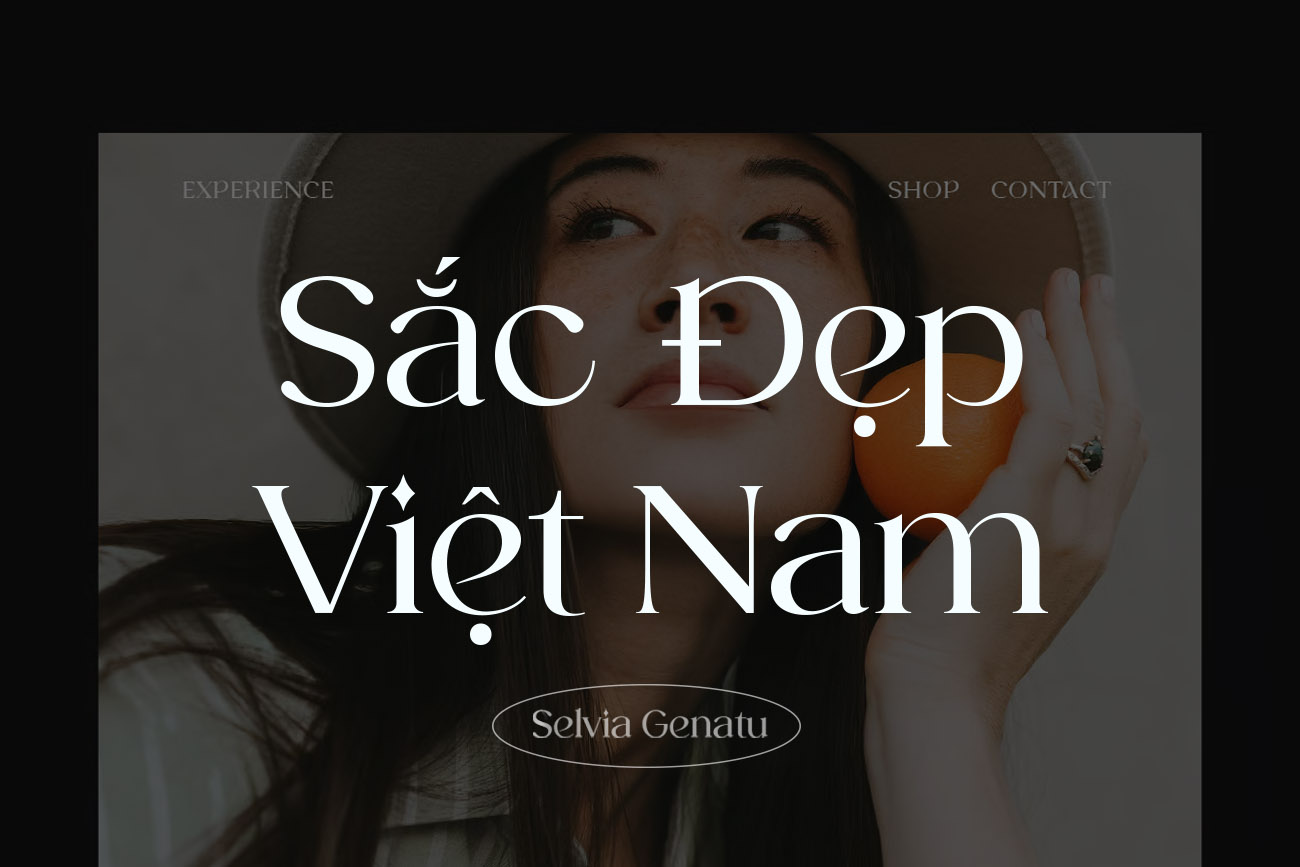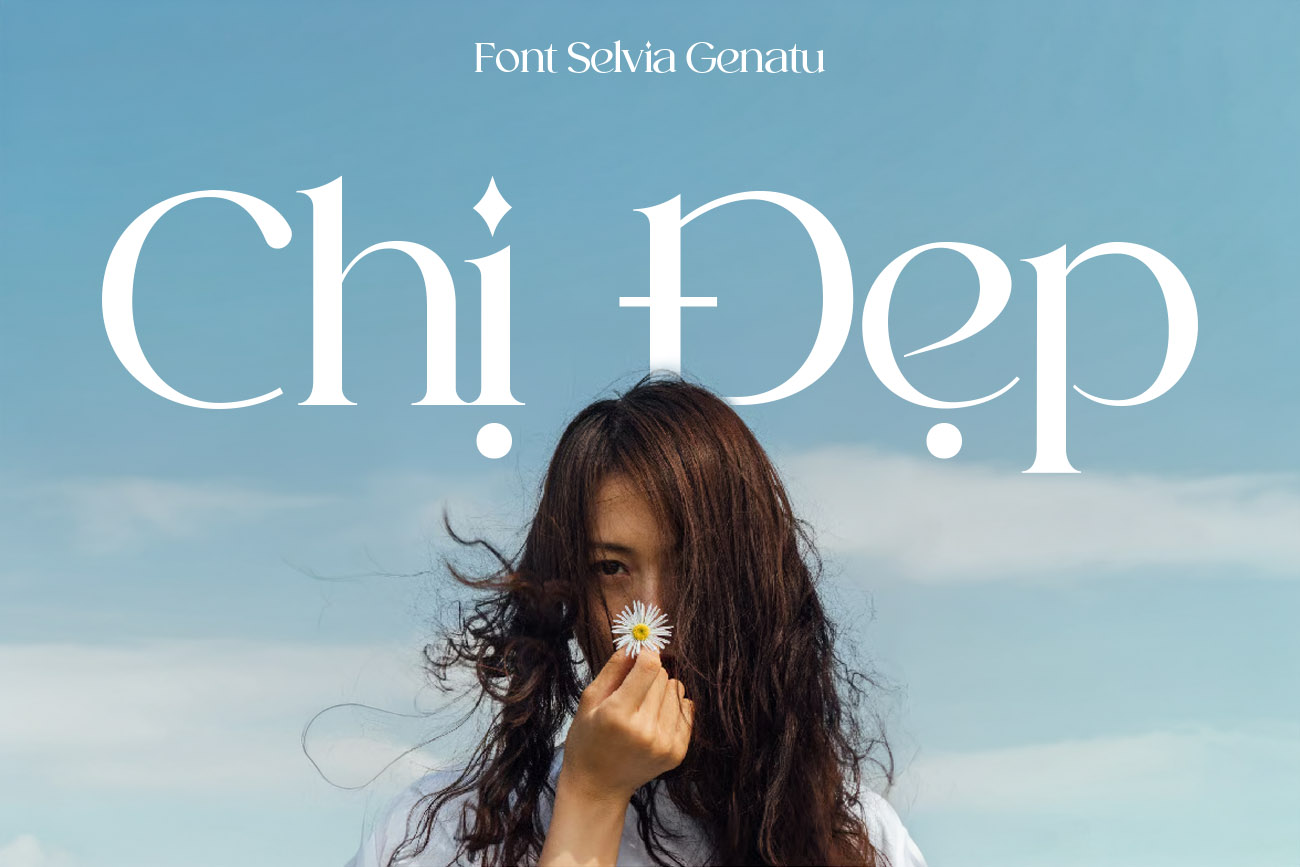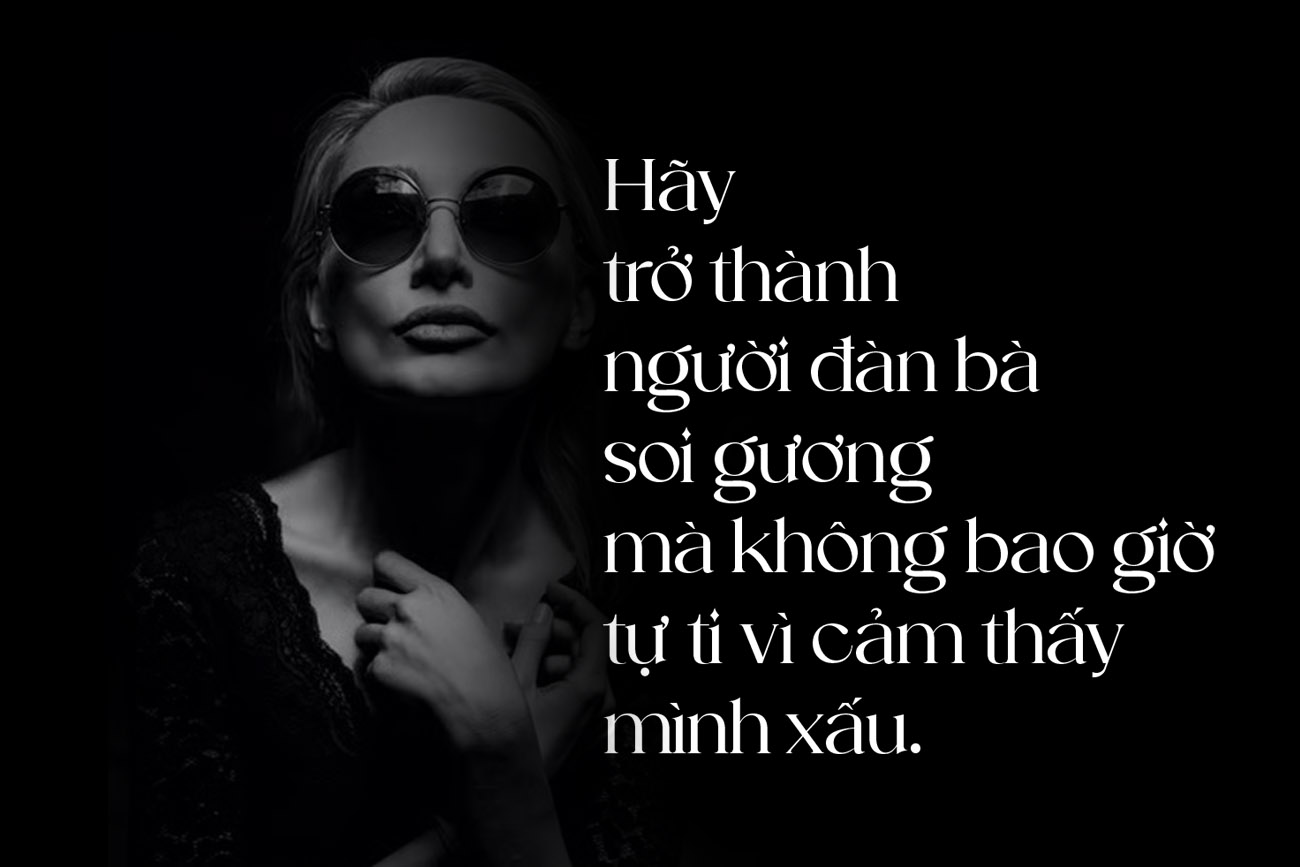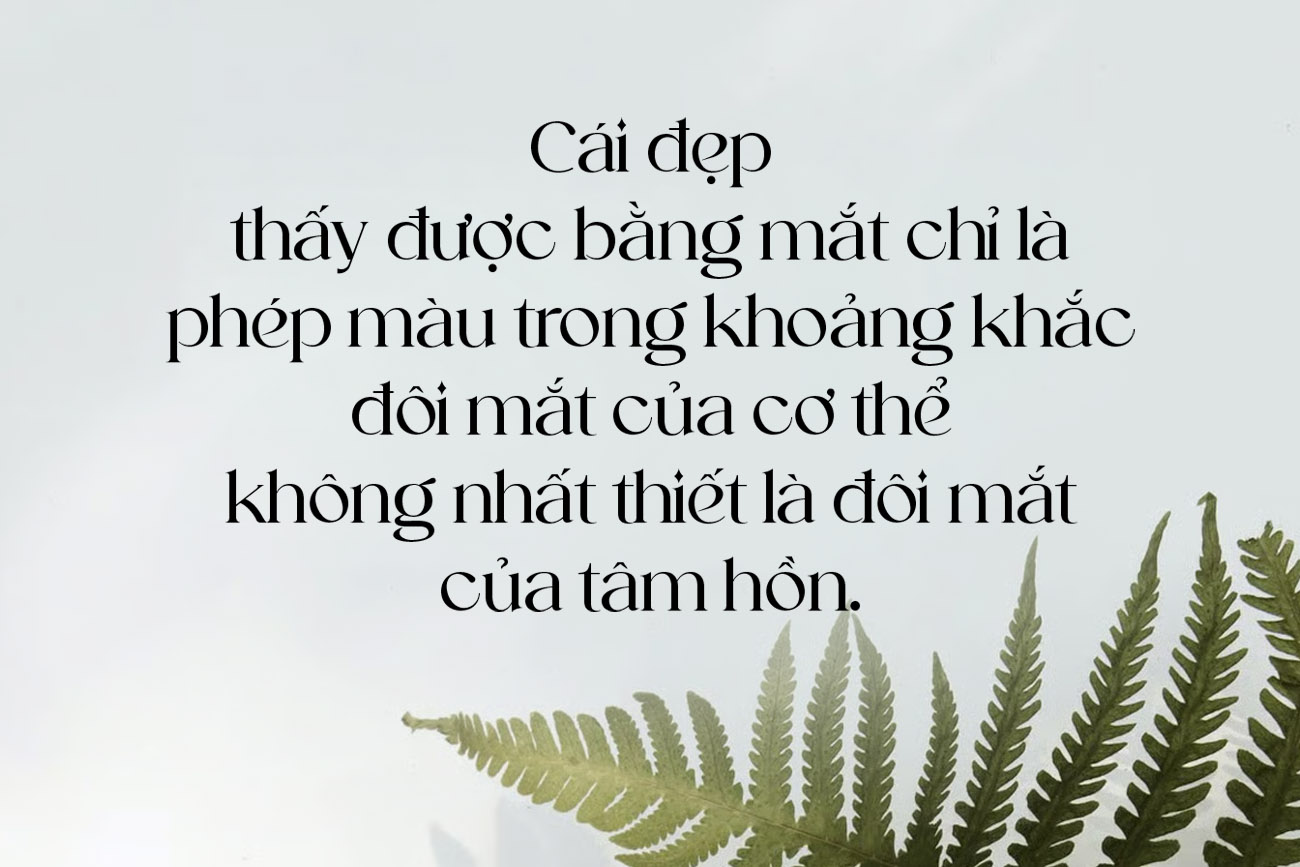
TH Selvia Genatu - Font chữ Serif Việt hóa cho thiết kế sang trọng
Trong thế giới thiết kế đồ họa không ngừng biến đổi, việc tìm kiếm một kiểu chữ vừa mang nét vintage, vừa đáp ứng được xu hướng thẩm mỹ đương đại là điều mà mọi Designer đều mong muốn. Hôm nay, chúng tôi xin giới thiệu đến cộng đồng sáng tạo bộ font chữ Việt hóa TH Selvia Genatu – một tác phẩm đầy tinh tế được Việt hóa bởi Team TH.
TH Selvia Genatu - Tuyệt phẩm Font chữ Serif Việt hóa cho thiết kế sang trọng
Vẻ đẹp giao thoa của Selvia Genatu
Được sáng tạo bởi Yukita Creative, Selvia Genatu nguyên bản là một đại diện xuất sắc cho dòng font chữ Serif (chân có gạch). Khác với những kiểu chữ Serif truyền thống có phần cứng nhắc, Selvia Genatu sở hữu những đường nét thanh mảnh, uyển chuyển với độ tương phản cao giữa các nét thanh và nét đậm.
Đây là một font chữ hiện đại mang trong mình hơi thở của sự sang trọng và đẳng cấp. Các ký tự được thiết kế với những đường cong mềm mại, kết hợp cùng các nét nối (ligatures) độc đáo, tạo nên một tổng thể hài hòa, tựa như những dải lụa lướt nhẹ trên bản thiết kế. Chính vì vậy, Selvia Genatu cực kỳ phù hợp cho các dự án yêu cầu tính thẩm mỹ cao như: thiết kế logo thương hiệu thời trang, tạp chí, thiệp cưới, bao bì mỹ phẩm hay các tiêu đề website cần sự ấn tượng.
TH Selvia Genatu - Tuyệt phẩm Font chữ Serif Việt hóa cho thiết kế sang trọng
Phiên bản Việt hóa hoàn chỉnh từ Team TH
Mặc dù phiên bản gốc từ Yukita Creative đã rất xuất sắc, nhưng rào cản ngôn ngữ thường khiến các Designer Việt gặp khó khăn khi xử lý các dấu câu. Hiểu được điều này, Team TH đã thực hiện việt hóa bộ phông chữ này dưới tên gọi TH Selvia Genatu.
Điểm đặc biệt của phiên bản font chữ Việt hóa này nằm ở sự chỉn chu trong từng dấu tiếng Việt. Team TH không chỉ đơn thuần là thêm dấu, mà còn tinh chỉnh lại khoảng cách (kerning) và vị trí đặt dấu sao cho cân đối nhất với cấu trúc đặc trưng của bộ font gốc. Điều này đảm bảo rằng khi bạn gõ tiếng Việt, dòng chảy của văn bản vẫn giữ được sự liền mạch và tính nghệ thuật vốn có của Selvia Genatu.
TH Selvia Genatu - Tuyệt phẩm Font chữ Serif Việt hóa cho thiết kế sang trọng
Lời kết
TH Selvia Genatu là sự lựa chọn không thể bỏ qua nếu bạn đang tìm kiếm một font chữ Serif mang phong cách thanh lịch để nâng tầm các dự án thiết kế của mình. Sự kết hợp giữa tư duy thiết kế của Yukita Creative và kỹ thuật xử lý của Team TH đã tạo nên một công cụ đắc lực cho cộng đồng Designer Việt.
Hy vọng bộ font chữ hiện đại này sẽ mang lại nguồn cảm hứng mới mẻ cho các tác phẩm sáng tạo sắp tới của bạn. Hãy sử dụng nó một cách hiệu quả để tạo ra những thiết kế mãn nhãn nhất.